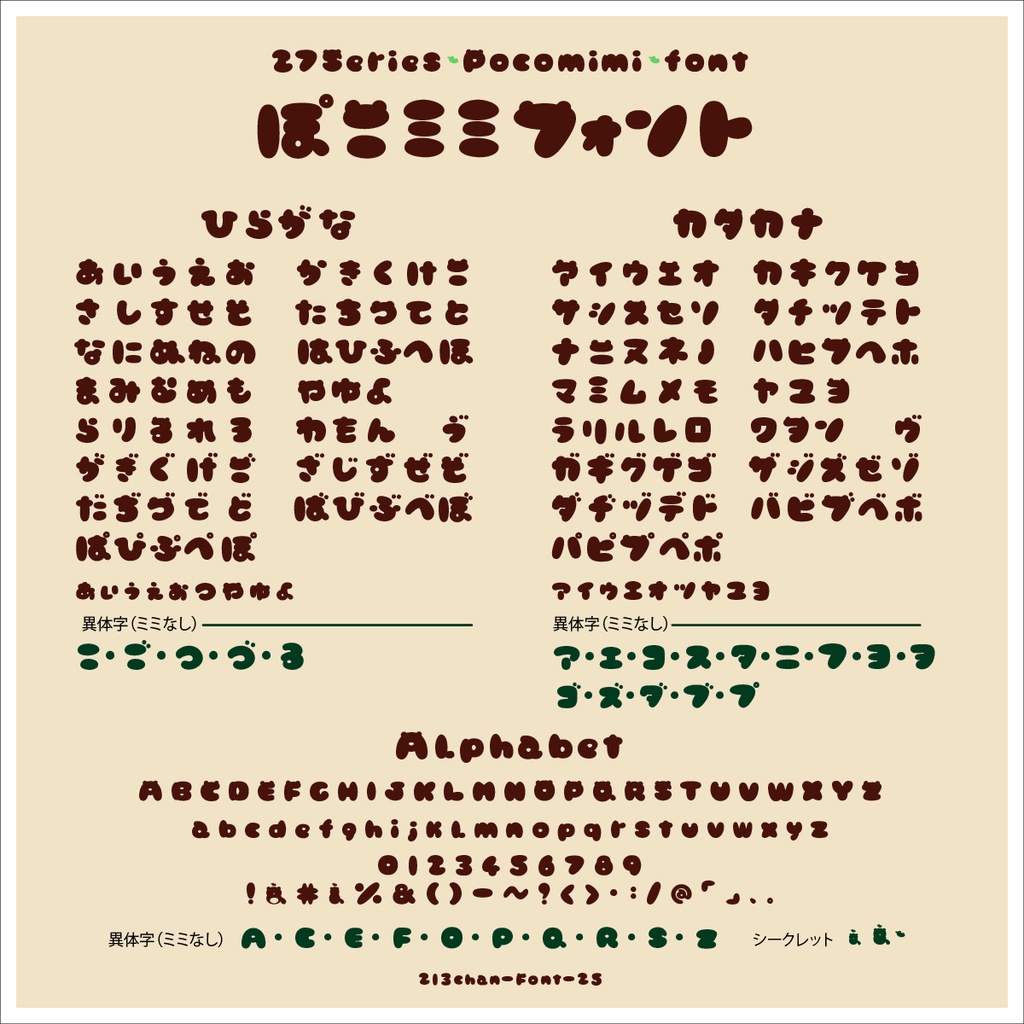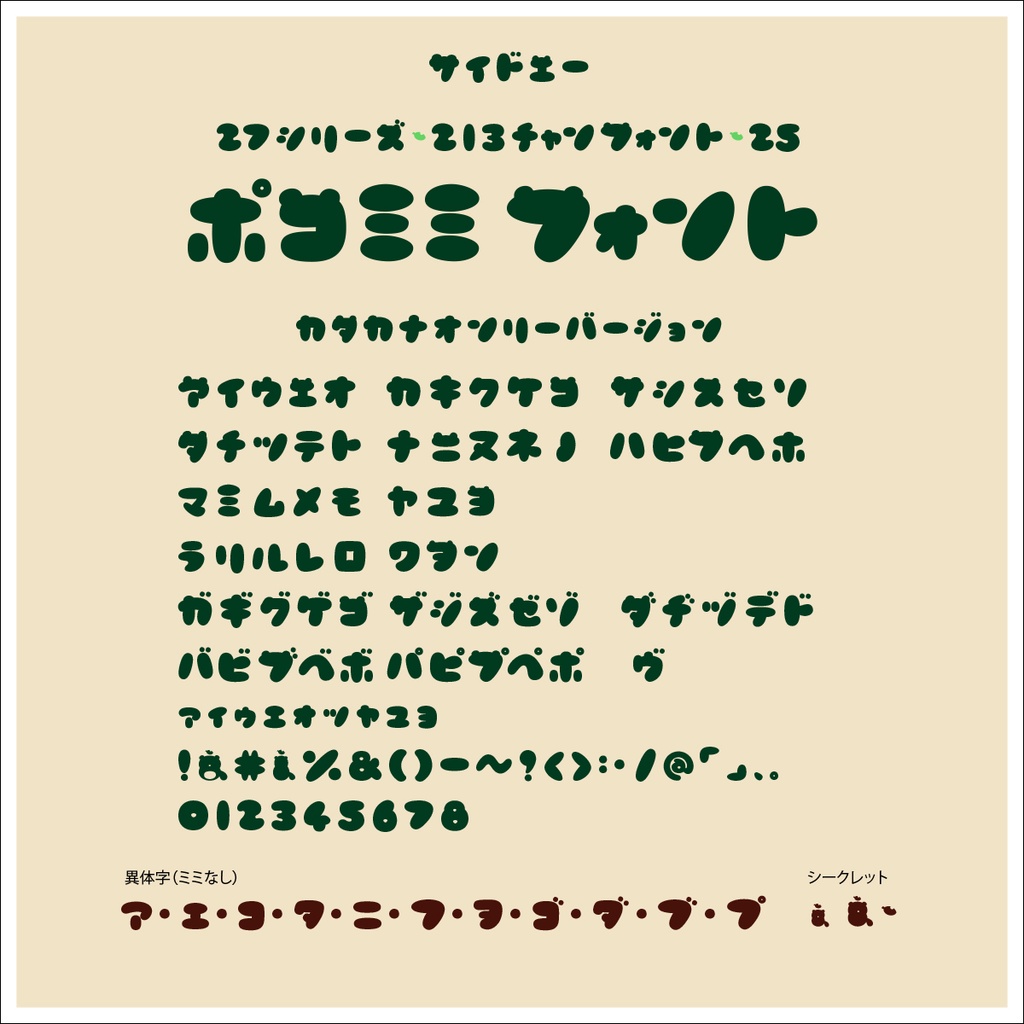
27-nina-pocomimi_font(ぽこミミフォント)【商用可】
27-nina-pocomimi_font(ぽこミミフォント)は213ちゃんが作った25個目の 商用可能な、たぬきのミミがついた可愛いフォントです! ミミがない文字も たぬきっぽい、ぽってりした愛らしいフォントです。 異体字としてミミがない字も選べます。 カタカナのみの、フリーフォント版のお試しで よかったら有料版をおすすめします! ※本文組書体ではないので、縦組みは困らない程度に使えます。横組推奨 ぽこミミフォントは9/24(水)リリース日から24時間半額にしますが 9/26(金)びーんずフォントとぽこミミフォントのペア2書体入ったお得な 2書体同梱版をリリースいたします。 どっちもほしい!方は金曜をお待ちください! 無料お試しフリーフォント版:【商用可】 27-nina-pocomimiA カタカナ・数字記号のみ版フリー 声援:有料DLで応援!【商用可】 27-nina-pocomimi 欧文(大小)・ひらがな・カタカナ・数字・記号 印刷物・ゲームやWeb、YouTubeのサムネイルやタイトルデザインなどにいかがでしょうか? 基本フリーですが、当フォントを利用した制作物などを、SNSで教えてくれると励みになります 制作note https://note.com/sweet_2727/n/ncb67d744a94f 【収録内容】欧文(大小)・ひらがな・カタカナ・数字・記号 【Readme】フォントご使用上の注意 ・フォントの著作権は、213ちゃんに帰属します。 ・可愛がってくださるとうれしいです。 ・無断転載・再配布は堅くお断りいたします。 ・DLしたフォントに起因する損害は補償致しかねますので予めご了承ください。 ・使用する際の不明点はお問い合わせ先にご連絡ください。答えられる範囲でお返事いたします。 英文 This font (213chan font) is a free OpenType font that can be used for commercial and personal web and print designs. Please take care of me. Font copyright belongs to 213chan. Unauthorized reproduction, redistribution, resale, and trademark registration of logos created using fonts is strictly prohibited. Please note that we cannot compensate for damage caused by DL fonts. Please note that we do not provide support regarding installation or usage.